“자네 무슨 일 하나?” 주변 어르신들은 사회 초년생이 된 나를 무척 궁금해하셨다.
디자인 공부를 한다던 녀석이 어떤 직장에 들어갔는지, 월급은 잘 받는지 궁금하실 테니 둘러 물어보신다. “네, 글자 디자인하고 있습니다.”라고 답하니, “아하. 간판 만드는 구만” 하신다. 당시 여느 어르신들의 생각은 글자 하면 간판이 떠오르셨나 보다.
글자 디자인(폰트 디자인)을 시작하면서 주변의 글자를 유심히 보게 되고, 좋고 나쁨에 대해 판단하기를 수년간, 가장 눈에 띄는 주위의 글자는 역시 간판이었다. 물론 글자의 표현은 다양한 곳에서 보이지만, 유독 화려하고 멋들어진 간판을 보면 왠지 더욱 설레었던 것 같다. 결국 글자를 디자인하던 몇 년 차부터 간판 전문잡지에 글자 디자인 관련 원고를 수년간 올리게 되었다. 이제 와서 생각하면 열정 넘치는 젊은 디자이너의 자기 자랑 같아 무척 낯부끄럽지만, 다행인 것은 간판에서의 글자 디자인은 매출에 큰 영향이 있다는 것을 누구보다도 잘 알게 된 중요한 시기였다.
당시 잡지사에서 주관하는 세미나에서 강의를 하게 되었고, 전문 간판업체에 종사하시는 많은 분들이 참석하여 글자 디자인에 대해 들어 주셨다.
젊은 디자이너의 보잘것없는 강의를 열심히 들어주시던 분들의 질문 중 ‘좋은 글자는 어떤 것인가?’라는 질문에 좋은 ‘글자는 이래야 한다 저래야 한다.’며 쉽게 떠들었던 기억이 있다. 지금 생각하면 민망하여 참을 수 없지만 이제는 이렇게 답하지 않을까?
"목적에 맞게 잘 고르시면 그것이 좋은 글자입니다."
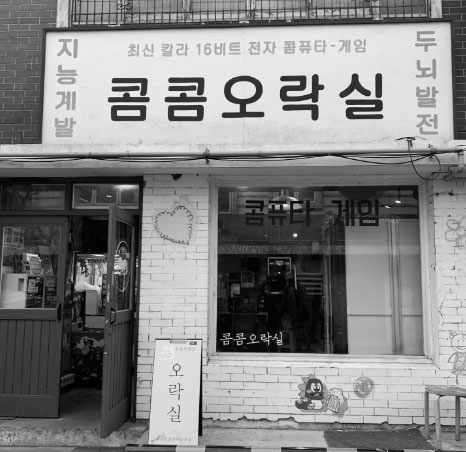
요즘 회사 근처에 청년들이 진을 치고 장사하는 골목이 만들어졌다. 삼 년여 된듯한데, 주변에 많은 먹거리 집이 생긴다는 것은 무척 반가운 일이다. 점심 메뉴를 고르는 일이 얼마나 스트레스를 주는지 많은 직장인들은 잘 알 것이다. 그런데 흥미로운 것은 새로 생긴 가게들의 간판이 그동안의 무뎌진 감각을 깨워주는 자극제가 된다는 것이다. 이제껏 깔끔하고 잘 정돈된 간판이 좋다는 생각을 180도 바꿔 주는 고마운 일들이 생겨나기 시작했다.
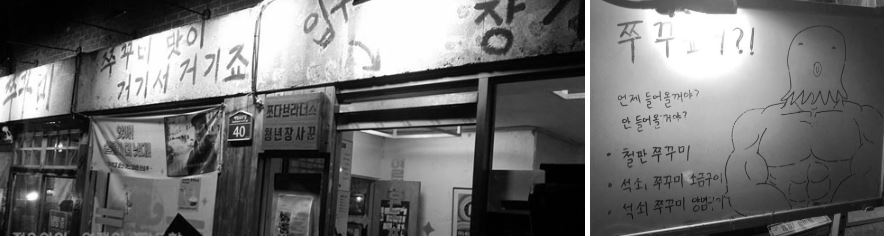
‘열정도’ 지금은 꽤 유명해서 저녁이면 동네마다 새로 생긴 청년들의 식당에는 많은 손님들로 북적거린다. 레트로 이미지의 간판과 인포메이션은 오히려 나이 든 중년의 손님보다 젊은이들에게 인기가 많다. 꾸밈없이 급하게 혹은 성의 없이 만들어진 듯한 간판이 꽤 매력적으로 다가오는 이유는 무엇일까?
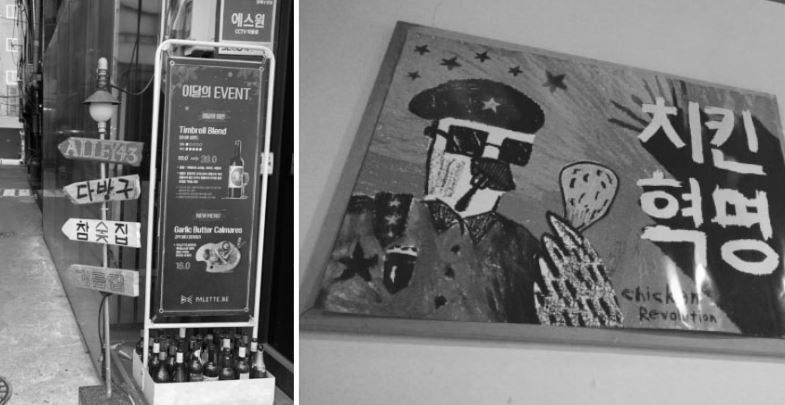
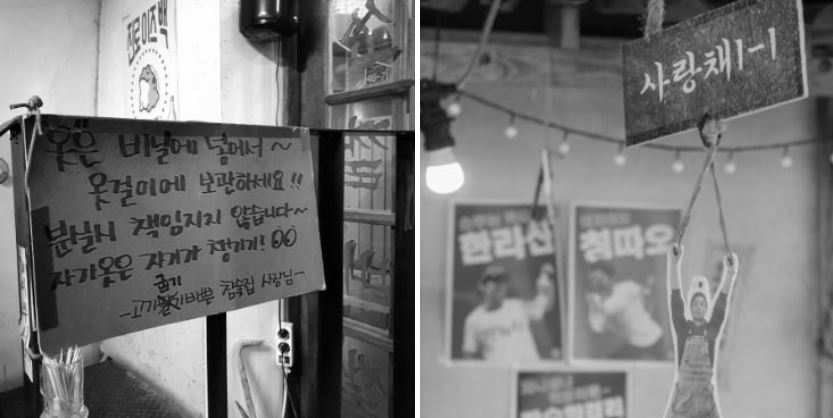
여기서는 열정도 거리의 간판과 정보물들이 좋거나 나쁘다를 이야기할 것은 아니다. 왜냐하면 개인별 취향의 차이가 있기 때문이다. 오늘도 거리에서 간판을 보며 여유를 느끼는 점심시간을 감사히 여긴다.